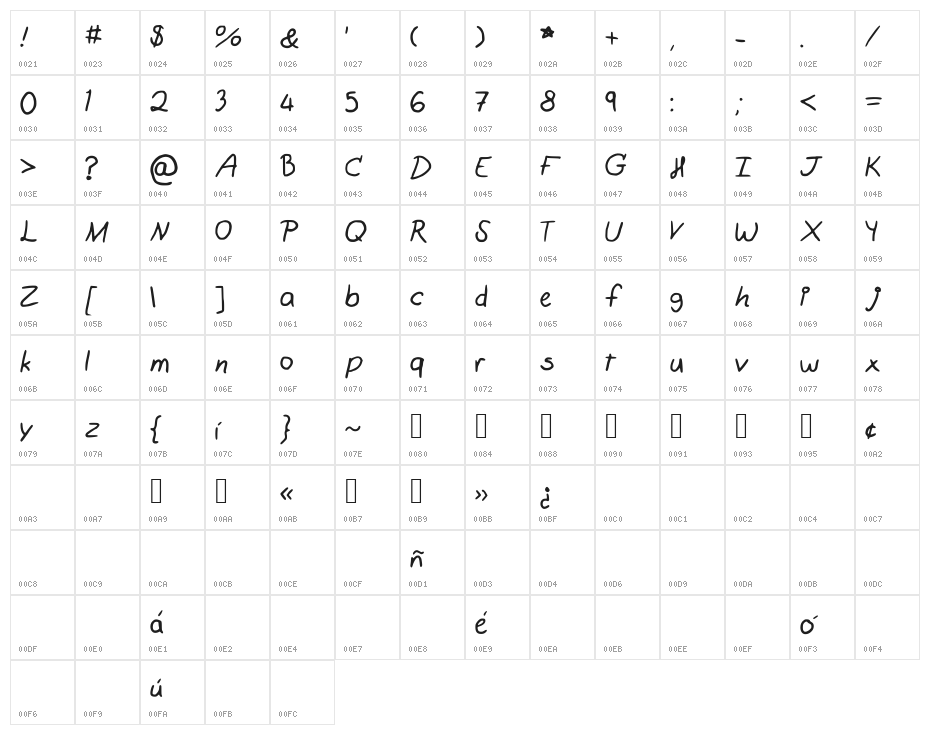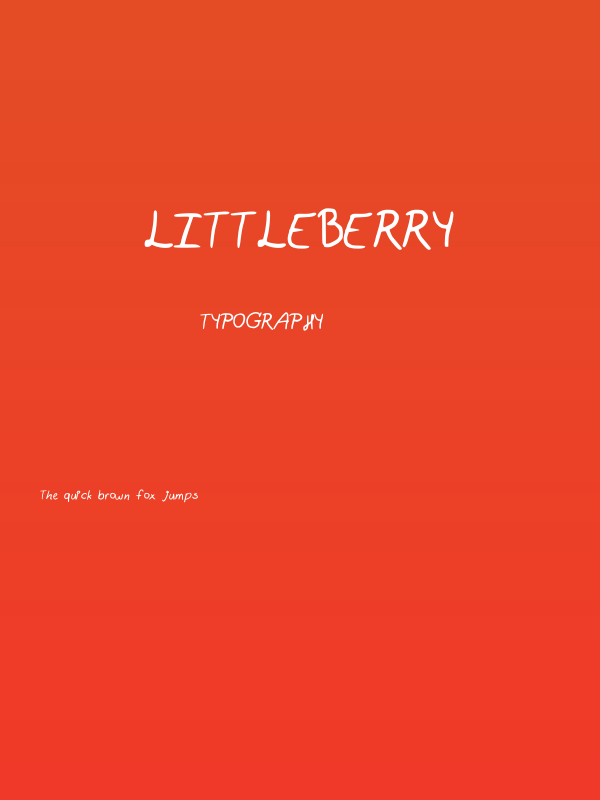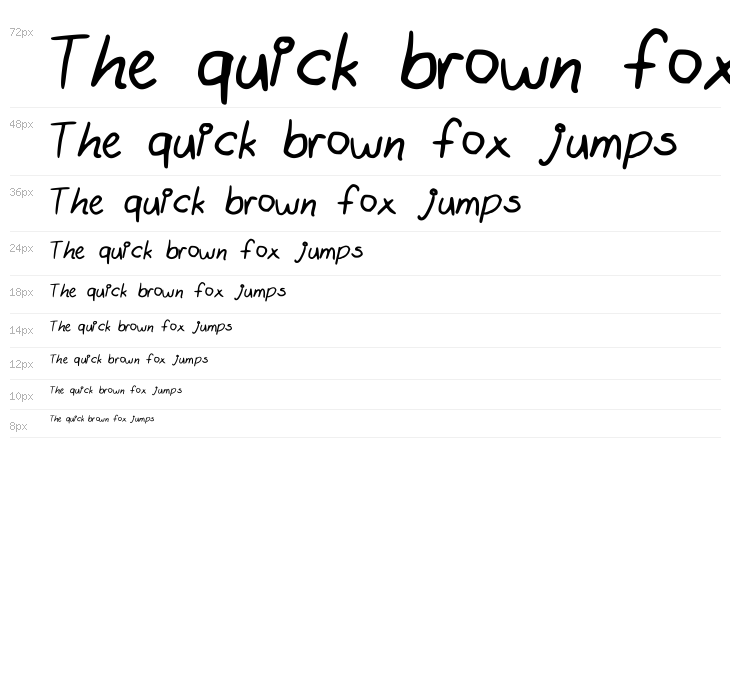
LittleBerry Font
| Gesamtstil | Casual, Playful |
| Anwendungsfall | Greeting cards, Children's books, Playful branding |
| Vorgeschlagene Projekte | Ideal for greeting cards, children's books, playful branding, and social media graphics. |